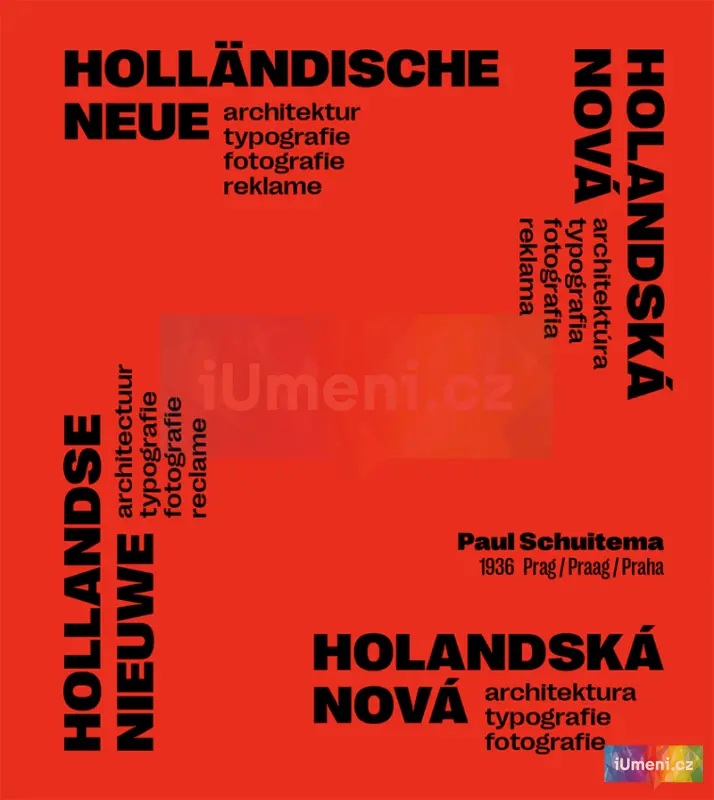
Holandská nová architektura, typografie, fotografie
Vícejazyčná publikace se soustředí na problematiku avantgardní typografie. Využívá k tomu tvorby výjimečné umělecké osobnosti – nizozemského designéra, fotografa a filmaře Paula Schuitemy, již zasazuje do rámce dobových tendencí a proudů pozorovaných na území širší střední Evropy.
Především ale přináší překlad jeho klíčové stati a připomíná přirozená sepětí československé a holandské avantgardy meziválečného období.Paul Schuitema je jednou z důležitých a formativních osobností evropského prostředí 1. poloviny 20. století. Proslul nejen jako praktik, ale také teoretik, entreprenér a spojovatel kulturních i sociálních prostředí. Památná je jeho cesta do Československa, které navštívil v roce 1936. Schuitema tehdy přijel na pozvání Františka Kalivody, aby v Brně a Praze přednášel o Nové fotografii, využití fotografie v grafickém designu a o holandské filmové avantgardě.
V působivém grafickém řešení publikace zaznívají ozvuky historické revoluce, přičemž je testována její udržitelnost.